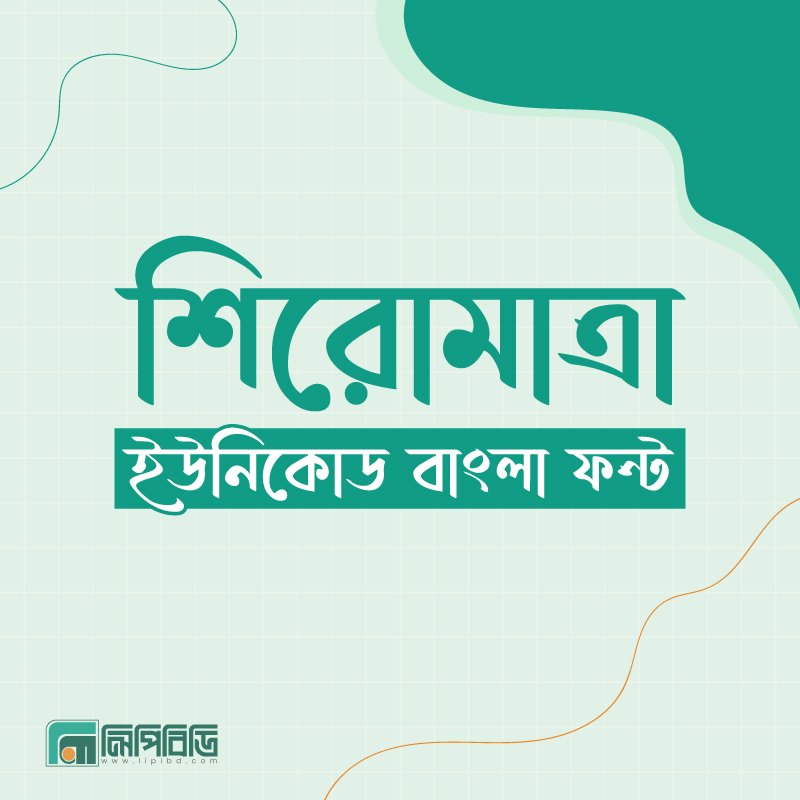
শিরোমাত্রা ইউনিকোড (ShiroMatra Unicode Premium Font)
শিরোমাত্রা ইউনিকোড একটি প্রিমিয়াম মানের বাংলা ইউনিকোড ফন্ট, যা তৈরি করা হয়েছে আধুনিক টাইপোগ্রাফি এবং ঐতিহ্যবাহী বাংলা অক্ষরের সৌন্দর্যকে একসাথে ধরে রাখার জন্য। এই ফন্টের প্রতিটি অক্ষর পরিষ্কার, ভারসাম্যপূর্ণ এবং নান্দনিকভাবে ডিজাইন করা, ফলে লেখা দেখতে হয় মার্জিত এবং পড়তে হয় আরামদায়ক।
বাংলা লেখার উপরের দাগ বা শিরোমাত্রাকে কেন্দ্র করে এই ফন্টের গঠন তৈরি করা হয়েছে। তাই বড় শিরোনাম, ব্যানার, বইয়ের কভার, পোস্টার বা সোশ্যাল মিডিয়া ডিজাইনে এটি ব্যবহার করলে লেখার মধ্যে একটি শক্তিশালী ও প্রফেশনাল উপস্থিতি তৈরি হয়।
বাংলা যুক্তাক্ষর, কারচিহ্ন এবং প্রয়োজনীয় গ্লিফগুলো এই ফন্টে সুন্দরভাবে সাপোর্ট করে, তাই দীর্ঘ লেখা টাইপ করলেও এটি স্বাভাবিক এবং পরিষ্কার দেখায়।
কেন শিরোমাত্রা ইউনিকোড ব্যবহার করবেন
বাংলা টাইপোগ্রাফিতে যারা প্রফেশনাল এবং আকর্ষণীয় লুক চান, তাদের জন্য শিরোমাত্রা ইউনিকোড একটি চমৎকার পছন্দ। এটি শুধু একটি ফন্ট নয়, বরং এমন একটি ডিজাইন টুল যা আপনার লেখা এবং ডিজাইনকে আলাদা পরিচয় দিতে সাহায্য করে।
যেখানে সাধারণ ফন্টগুলো অনেক সময় সাধারণ দেখায়, সেখানে শিরোমাত্রা ইউনিকোড লেখাকে দেয় একটি শক্তিশালী উপস্থিতি এবং নান্দনিক সৌন্দর্য। তাই ক্রিয়েটিভ ডিজাইন, ব্র্যান্ডিং এবং প্রিমিয়াম প্রজেক্টের জন্য এই ফন্ট হতে পারে একটি আদর্শ সমাধান। ✨